文字はどこまでも生き残る
携帯電話におけるフォント革命
NTTドコモが、携帯電話に搭載する文字を一新する。その第1弾が、2008年11月に発売されたシャープ製「SH-01A」だ。デフォルトとして新たに加えられた書体はAXIS Font。美しいユーザーインターフェースをつくるには美しいフォントが不可欠だと考えたtakramの田川欣哉氏と、AXIS Fontを携帯電話向けにリファインしたタイプデザイナーの鈴木 功氏が、手のひら上の文字の未来を占う。
画面の8割は文字
携帯電話の画面上で、複数のアプリケーションが稼働するプラットフォームをつくりたい。田川欣哉氏がそんなNTTドコモの要望に応じてユーザーインターフェースの開発を始めたのは数年前のこと。プロトタイプの画面表示用書体として、田川氏は自分の好みから何気なくAXIS Fontを使っていた。ところが製品化に際して、書体を既存のビットマップ・フォントに置き換えたとき、デザインのクオリティが大きく損なわれていることに驚いたのだという。
田川氏は考えた。携帯電話画面上におけるデザイン構成要素の8割は文字。その文字を置き去りにして他の部分をいくらきれいにしたところで、面積でいえばせいぜい2割程度の貢献しかない。携帯電話という製品の完成度を高めるのに、いちばん近道なのは画面の文字を美しくすることではないのだろうか。
新しいインターフェースにふさわしい文字を搭載しよう。田川氏は、WOWの鹿野 護氏らデザインプロジェクトのメンバーとともに、NTTドコモのプロジェクト関係者たちに熱弁した。
「この小さな画面を、銀座の一等地だと想像しましょう。ここでビジネスをする以上、その要素である1文字1文字には重要な価値が備わっているはずです。表示可能な文字数が増えたり、美しさや読みやすさが洗練されれば、携帯電話の価値は大きく向上するのではないでしょうか」。
書物を読むとき、私たちはそこに使用されている書体や文字組みからブランドイメージを感知している。朝日新聞と読売新聞、岩波文庫と新潮文庫では、それぞれ”立ち上がる香り”が異なるのだ。そこでドコモらしさとは何かを議論した田川氏や鹿野氏らは、「オーセンティックで、かつテクノロジーの先駆者」であるというイメージに合致する書体選びに取りかかった。新書体を開発するという選択肢も、この段階ではあったという。
「AXIS Fontは、ひとりの書体作家により雑誌の専用書体としてつくられたという『志の高さ』が際立っていました。また携帯電話開発のような大事業では、それぞれのステージを担当するクリエイター全員に最良の仕事をしてもらうための環境が必要です。前提となるデザイン要素として良質の統一フォントのようなものがあれば、雰囲気に合ったものが出てきやすい。そのようにクリエイターやエンジニアのモチベーションを刺激してくれる書体は、AXIS Fontしかないだろうという話になったのです」。
NTTドコモはこれまでもフォントに関するいくつかの試みを行ってきたが、いずれも端末メーカーと個別に行ったものだった。それが今回はNTTドコモが自社でサービスとGUIを含むアプリケーションを開発し、端末メーカー各社に採用してもらうという、より主導権の強い開発形態にシフトしている。キャリア側が搭載書体を自らの問題として認識したことも、彼らの素早い決断を促したようだ。
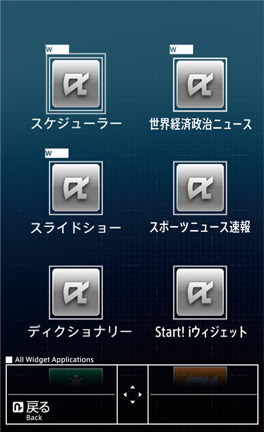
文字はもっと小さくできる
先端技術の進歩に気を配りながら、変わるものと変わらないものを見極める。田川氏はそのようにしてできる限り具体的な未来予想図を描く。「携帯電話の未来にどこまでも寄り添う不変の条件、それは僕らの手のひらの大きさです。この制約があることで、携帯電話の横幅は今よりさほど大きくならないでしょう。すなわち液晶画面の進歩は、画面の大きさではなく高精細化で示されることになります」。
事実、携帯電話の画素数はここ2年で約4倍に向上している。さらに画面の高精細化が進めば、それだけ文字を小さく鮮明に表示できるようになる。田川氏は文字の大きさがズーミングで自在に変えられるようなインターフェースを構想している。 「携帯電話で使われる文字はどんどん印刷物のクオリティに近づいていきます。文字は写真以上に液晶の高精細化を促す要因なので、液晶の進化とフォントへの関心の高まりは、とても相性がいい話題なのです」。
書体をブランドイメージに通じる経営資産と位置づけ、その運用法を議論する。このようにして世の中の文字を少しずつ美しくしていくことの意義は、何十年も先を見据えた文化的議論のなかで語られるべきテーマだと田川氏は信じている。「2009年からNTTドコモが発表する携帯電話の多くに、AXIS Fontが搭載される予定です。現代の子供たちにとって、携帯電話からインプットされる文字情報の量は、紙に印刷されたそれと比較しても、かなり多いのではないかと思います。利用者に日本語を大切に感じてもらえるような環境を提供するのも、ものづくりに関わる人間の責務だと思っています」
これまでにない緩やかさ
今回シャープ製SH-01AやSH-04A(09年2月発売)に搭載されたのは、AXIS Fontの等幅アウトラインおよびビットマップ版である。当初、田川氏が制作したプロトタイプの画面の一部には、AXIS Fontの長体バージョンである「コンデンス」が使われていた。そのコンデンスが搭載に至らなかったのは、文字詰めを適切に制御するラスタライザの開発が困難であったためだという。今後の課題は、文字幅や字詰めの最適化にある。
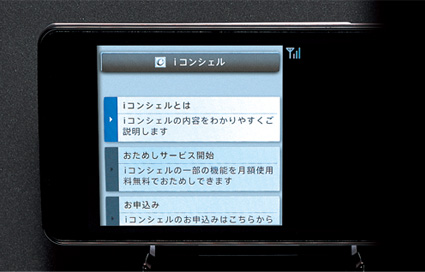
AXIS Fontは、他の書体よりも字面がやや小さめにつくられている。携帯電話の画面上で眺めてみると、同じ字詰めでもゆったりと文字を読ませてくれるのが印象的だ。逆に今までの携帯電話の文字が、いかに窮屈に表示されていたのかがわかる。技術上の問題から文字が読めないというトラブルを回避するため、端末メーカーは大きめの文字をぎっしりと詰め込む安全策をとってきた。しかし今後、画面が高精細化を辿れば、細くすっきりとした書体が好まれる可能性は高い。小さくなるほど読みやすさが際立つのもAXIS Fontの特長である。
世の中の文字が変わる契機
AXIS Fontの作者であるタイプデザイナーの鈴木 功氏は、今回のプロジェクトのためにAXIS Fontを携帯電話の環境に合わせて調整した。全文字のアウトラインデータ、合計7サイズのビットマップデータ、さらには282グリフの絵文字を今回新たに作成している。行間が狭い画面上でのオーバーラップを防ぐため、欧文のpやyなどがベースライン下へ飛び出し過ぎないよう細部のデザインも調整済みだ。
「AXIS Fontらしい、ゆったり感やすっきり感が表現できていると思いました。制作期間は3カ月でしたが、もっと時間があれば、『携帯電話らしさ』や『ドコモらしさ』にも踏み込みたかった。次のステップがあるのなら、コンデンスを中心としたカスタマイズにぜひ取り組みたいですね」。もともと本誌のためのフォントとして開発されたAXIS Fontだが、コンデンス書体、コンプレス書体といった長体のファミリーには、デジタル世代の新しい需要も見込んでいたと鈴木氏は語る。